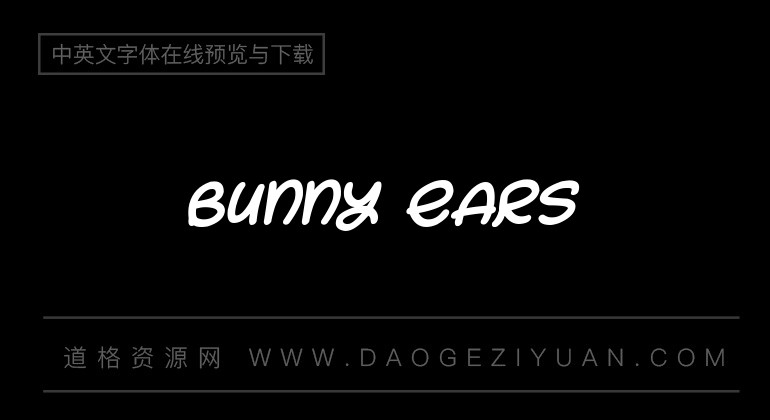
Bunny Ears
Bunny Ears 字体是一种可爱、活泼的手写字体,其设计灵感来源于兔子的耳朵形状。这种字体的特点是字母形状类似于手写体,但又具有一定的规律性和一致性,整体看上去非常可爱。Bunny Ears 字体非常适合用于与儿童和动物相关的设计项目,例如儿童书籍、玩具包装、卡片等等。这种字体也可以用于一些趣味性质的设计,例如网站的标语、简短的文章标题等等。总之,Bunny Ears 字体是一种非常有趣和独特的字体,可以为您的设计项目增添一份活泼和可爱的气息。
Bunny Ears是一款非常不错的手写艺术字体,具有很好的视觉感,适合于文化类的宣传设计、商业类品牌的广告和产品包装设计以及个性化文字排版等较多场景。